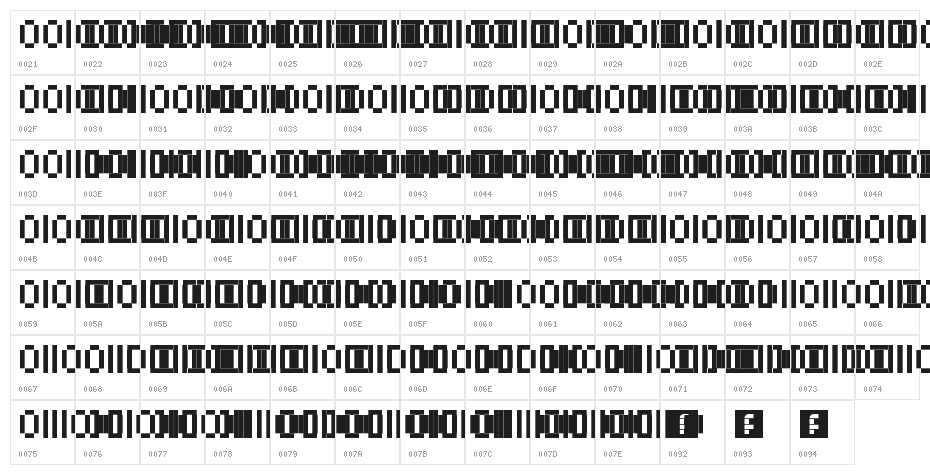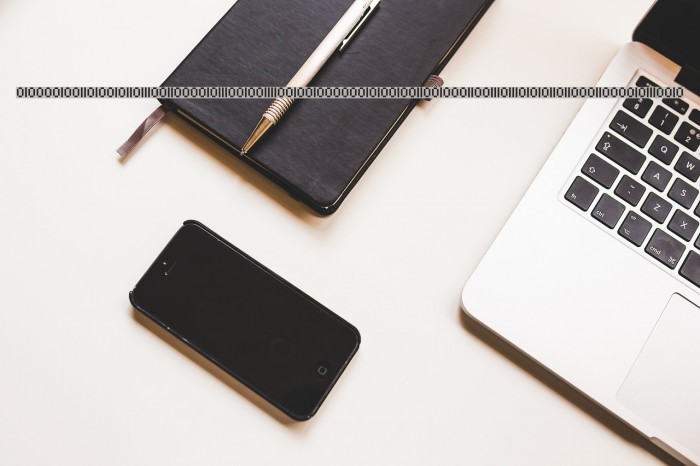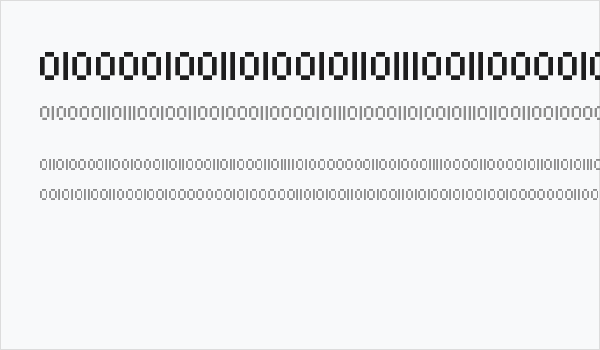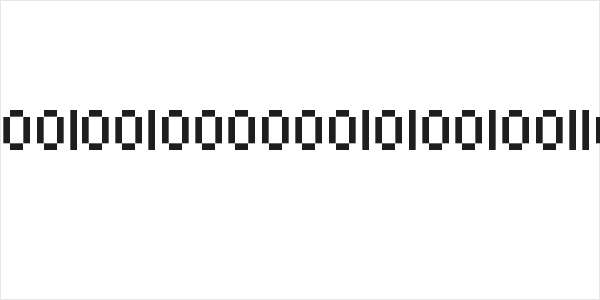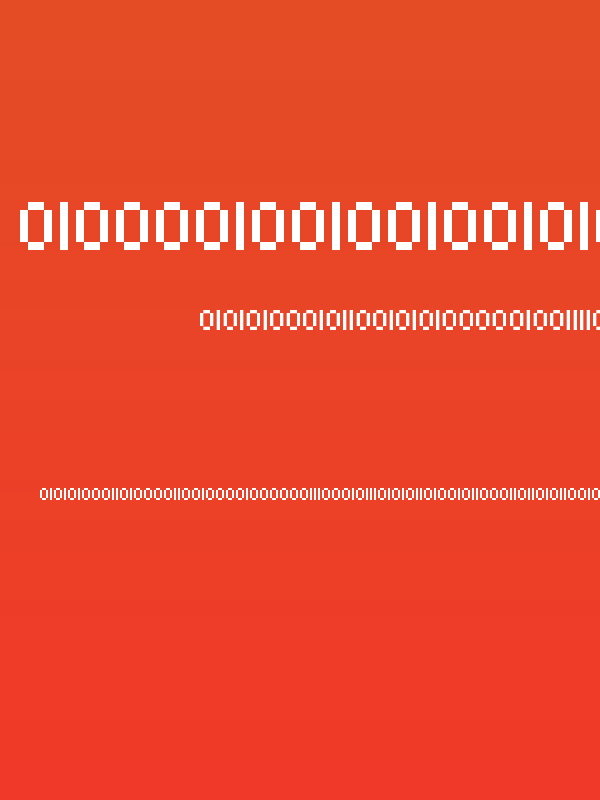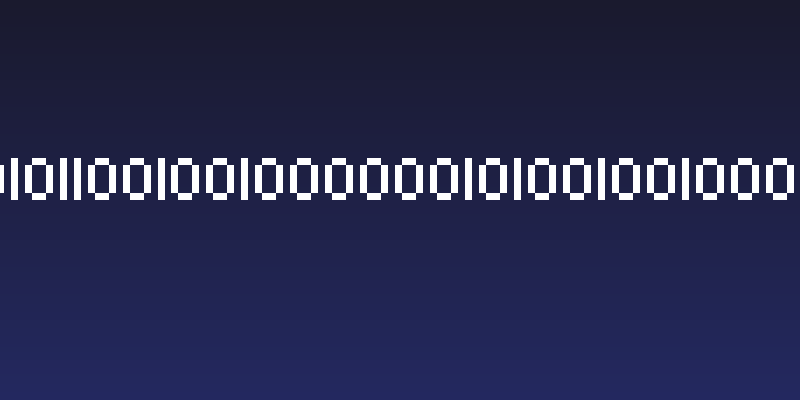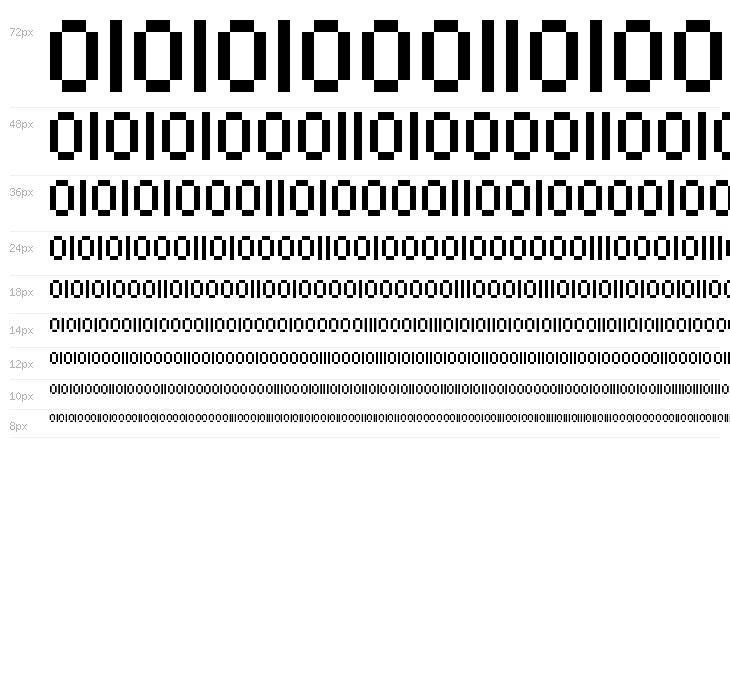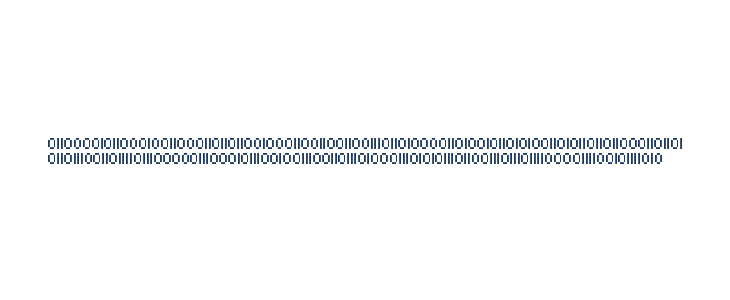
Binary Regular Font
| Caz de utilizare | Logos, Digital Art, Thematic Posters |
| Proiecte propuse | Ideal for digital art projects, tech-themed posters, or any design requiring a futuristic, computational aesthetic. |